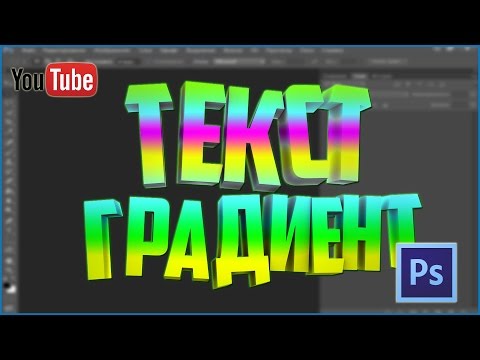
Создание градиентного шрифта в Photoshop: техники и советы
Хотите узнать, как создать уникальный эффект градиентного шрифта в Photoshop? В нашей статье мы поделимся техниками и советами, которые помогут вам достичь впечатляющего результата.
Выберите подходящие цвета для градиентного эффекта. Попробуйте сочетания теплых и холодных оттенков, чтобы создать интересный контраст и эффектное сочетание цветов.
Используйте инструменты Текст и Градиент в Photoshop для создания градиентного шрифта. Настройте направление градиента и регулируйте его насыщенность и прозрачность, чтобы достичь желаемого эффекта.
Экспериментируйте с различными шрифтами и их размерами. Большие и жирные шрифты будут хорошо смотреться с градиентным эффектом, в то время как тонкие и нежные шрифты могут создать более элегантный и изысканный вид.